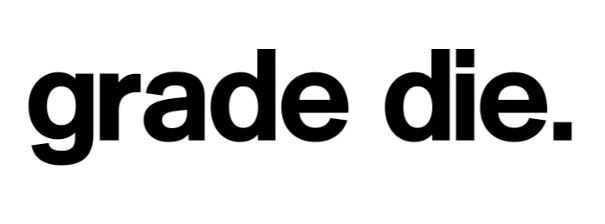
Helvetica ähnlich Schrift
Ich suche mal wieder eine Schrift,
diesmal die Schrift auf folgendem Bild.
Als erstes dachte ich Helvetica oder Arial, dann bin ich bei Akzidenz-Grotesk gelandet
und das stimmt aber alles nicht.
Vielleicht weiß es jemand von Euch.
irgendwie erinnert die mich stark an »Suisse BP Int’l Antique« allerdings hat die einen kleinen Abstrich beim a. Vielleicht wurde da aber auch manuell eingegriffen.
Aktiv Grotesk von Dalton Maag kommt dem auch sehr nahe.
Hier kommt das Beispiel her: